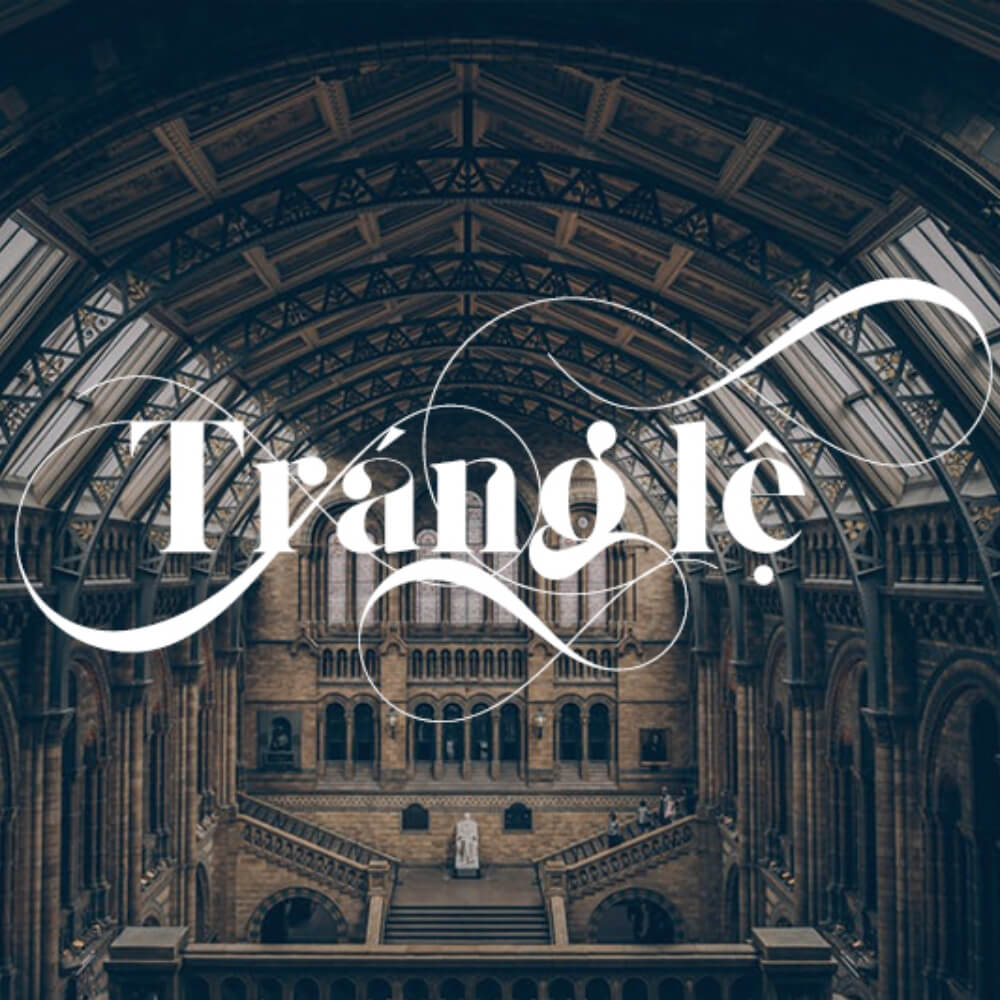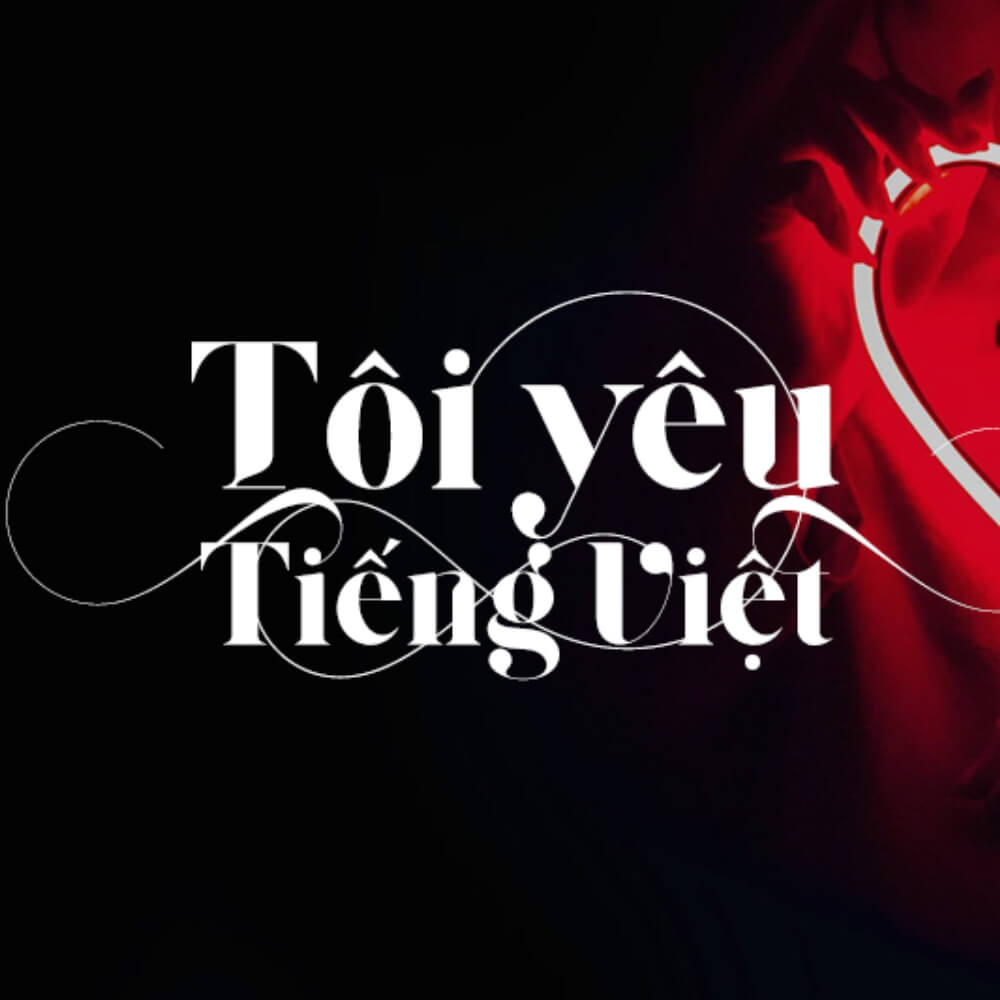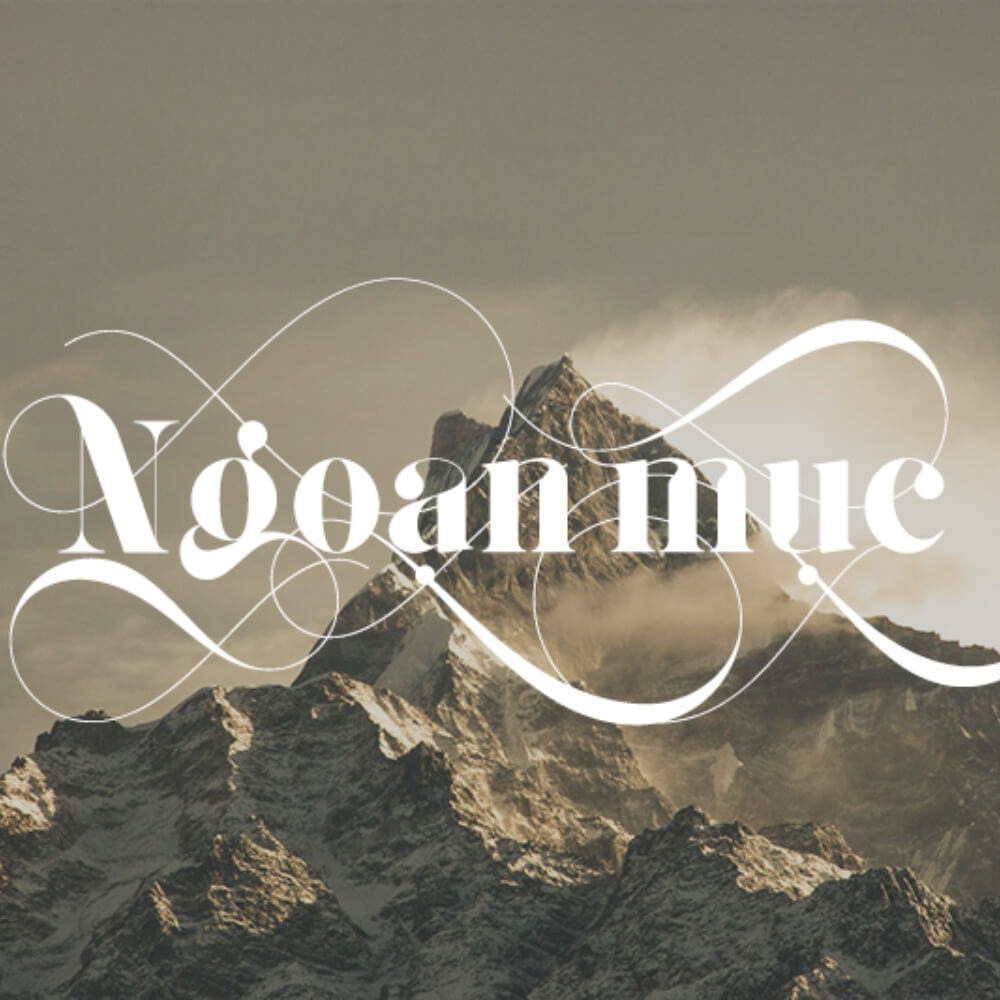
Font SVN Giaza việt hóa là lựa chọn lý tưởng cho những ai đang tìm kiếm một font display sang trọng, giàu tính nghệ thuật. Nhờ khả năng tùy biến linh hoạt và hỗ trợ tiếng Việt đầy đủ, font này đặc biệt phù hợp cho thiệp cưới, logo, menu và các thiết kế cao cấp cần tạo dấu ấn riêng biệt.
Đặc điểm của font SVN Giaza
SVN Giaza do AnthonyJJames thiết kế, Việt hóa bởi STYLEno.1 Fonts. Font là phiên bản Pro của Giaza phiên bản mở rộng với đầy đủ alternate characters và swash.
• 190 swash characters: Đây là điểm nổi bật nhất của Giaza Pro bộ ký tự thay thế khổng lồ cho phép tùy chỉnh từng chữ cái với nét bay, nét xoáy hoặc chi tiết trang trí khác nhau. Mỗi layout sẽ trông khác nhau dù dùng cùng một từ.
• Display font thiết kế cho legibility: Dù có nhiều swash, tác giả ưu tiên khả năng đọc, font không hy sinh legibility vì trang trí, phù hợp cho ứng dụng thực tế chứ không chỉ để trưng bày.
• Đa ngôn ngữ từ đầu: Giaza Pro được xây dựng với hỗ trợ nhiều ngôn ngữ Latin, bản SVN Việt hóa bổ sung thêm ký tự tiếng Việt có dấu theo chuẩn Unicode.
• Phù hợp nhiều ứng dụng: Theo tác giả, Giaza Pro phù hợp cho wedding, restaurant, editorial là ba lĩnh vực thiết kế có nhu cầu font trang trí cao nhất.
SVN Giaza với swash tinh tế tạo điểm nhấn sang trọng
Ứng dụng của font SVN Giaza việt hóa trong thiết kế
Font SVN Giaza việt hóa mang phong cách sang trọng, nghệ thuật, được ứng dụng rộng rãi trong các thiết kế cao cấp cần tạo điểm nhấn tinh tế và khác biệt.
• Thiệp cưới và stationery wedding: Bộ swash 190 ký tự cho phép tạo ra bộ thiệp cưới với từng ký tự được tùy chỉnh riêng, không bộ thiệp nào giống thiệp nào kể cả dùng cùng một font.
• Menu nhà hàng fine dining: Font tạo ra cảm giác sang trọng và curated phù hợp với menu dạng card hoặc menu dạng tờ rời cho nhà hàng từ mid đến cao cấp.
• Bìa tạp chí, editorial layout: Giaza Pro ở cỡ lớn trên bìa tạp chí lifestyle, thời trang hoặc wedding magazine tạo ra điểm nhấn tiêu đề có tính nghệ thuật cao.
• Logo thương hiệu mỹ phẩm, spa, boutique: phong cách trang trọng nhưng không cứng nhắc phù hợp với thương hiệu muốn định vị trong phân khúc premium mà vẫn thân thiện và tiếp cận được.
Giaza display font nổi bật cho tiêu đề và logo thương hiệu
Lỗi thường gặp khi dùng font SVN Giaza
Dưới đây là các lỗi thường gặp khi dùng font SVN Giaza việt hóa mà nhiều designer dễ mắc phải, ảnh hưởng trực tiếp đến chất lượng và tính thẩm mỹ của thiết kế.
• Dùng Giaza cho nội dung dài. Dù legibility tốt hơn nhiều font trang trí khác, Giaza vẫn là display font — chỉ dùng cho tiêu đề, tên thương hiệu và điểm nhấn, không dùng cho đoạn văn dài.
Font Giaza phù hợp thiệp cưới menu và thiết kế cao cấp
Font SVN Giaza việt hóa in đẹp nhất trên chất liệu nào?
Giấy couche mịn hoặc giấy mỹ thuật có bề mặt phẳng. Chi tiết swash tinh tế của Giaza cần bề mặt in sạch để hiện rõ — tránh in trên giấy có texture thô hoặc kraft không tráng phủ.